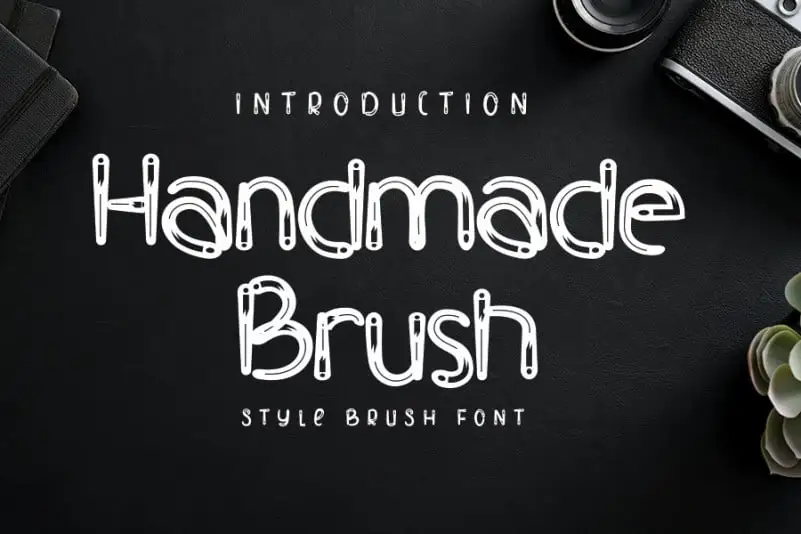
A Handmade Brush Font é uma elegante escolha para designers visuais apaixonados por personalidade. Inspirada no estilo das caligrafias mais refinadas, essa fonte mantém sua sofisticação clássica enquanto se atualiza e permanece fresca e vibrante. Seu carácter versátil a torna perfeita para uma ampla gama de ideias criativas, desde selos e títulos até papelaria e embalagens. Seja você um designer profissional ou um amador em hobby, essa fonte é o elemento ideal para dar um toque único e pessoal aos seus projetos. Engane-se apenas um pouco, deixe sua marca e divirta-se com a Handmade Brush Font.